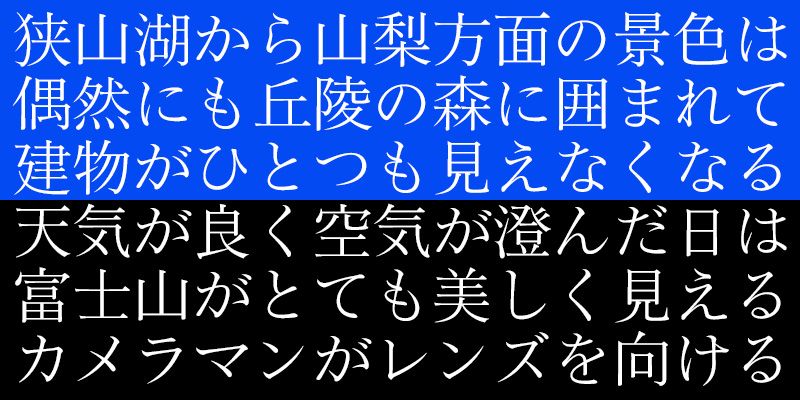
Il Seiwa-do Mincho-tai è stato prodotto come un versatile carattere tipografico in stile Mincho, che può essere utilizzato efficacemente per molti scopi, da testi per libri e riviste, e opuscoli contenenti lunghi blocchi di testo. Mentre ci sono vari tipi di carattere Mincho, lo Seiwa-do Mincho-tai è progettato con un ritmo e un flusso coerenti per sedersi esattamente tra i caratteri Mincho, rispettando e preservando la qualità stilistica dei tradizionali caratteri Mincho. Grazie alla forma autentica e leggibile delle lettere e all’equilibrio ottimale tra le forme kanji e kana, questo carattere intuitivo consente una lettura senza stress.
Il font Seiwa-do ha prodotto la serie di caratteri Seiwa-do Mincho-tai per ricercare la bellezza e la leggibilità del testo impostato in un carattere tipografico in stile Mincho progettato per il corpo del testo. In molti casi, la leggibilità è il fattore più importante quando si compone il testo per libri, riviste e opuscoli, anche se ancora oggi, ci sono un numero limitato di caratteri tipografici in stile Mincho destinati al corpo del testo. Seiwa-do Mincho-tai è disponibile come nuova aggiunta alla categoria di caratteri tipografici stile Mincho, che offre più opzioni per i progetti tipografici.